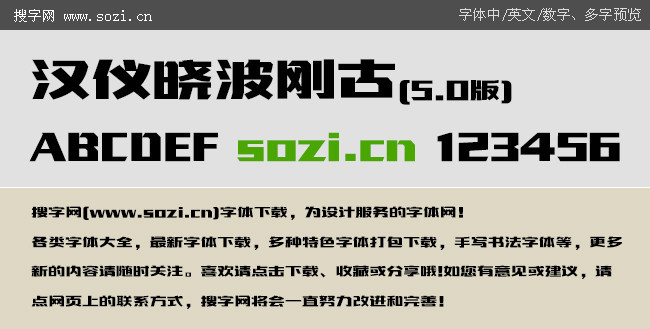
漢儀曉波剛古5.0
搜字網(wǎng)提供一款漢儀曉波剛古5.0字體下載,漢儀曉波剛古是一款漂亮的藝術(shù)字體。由漢儀曉波工作室出品,漢儀曉波鋼古是一款有著強烈鋒利感的字體,它本身筆畫厚重,更具力量感,適用于各類標(biāo)題字,海報設(shè)計,游戲動漫設(shè)計,企業(yè)標(biāo)準(zhǔn)字的應(yīng)用。(本字體為個人非商用版,如需要商用請聯(lián)系漢儀公司購買版權(quán))